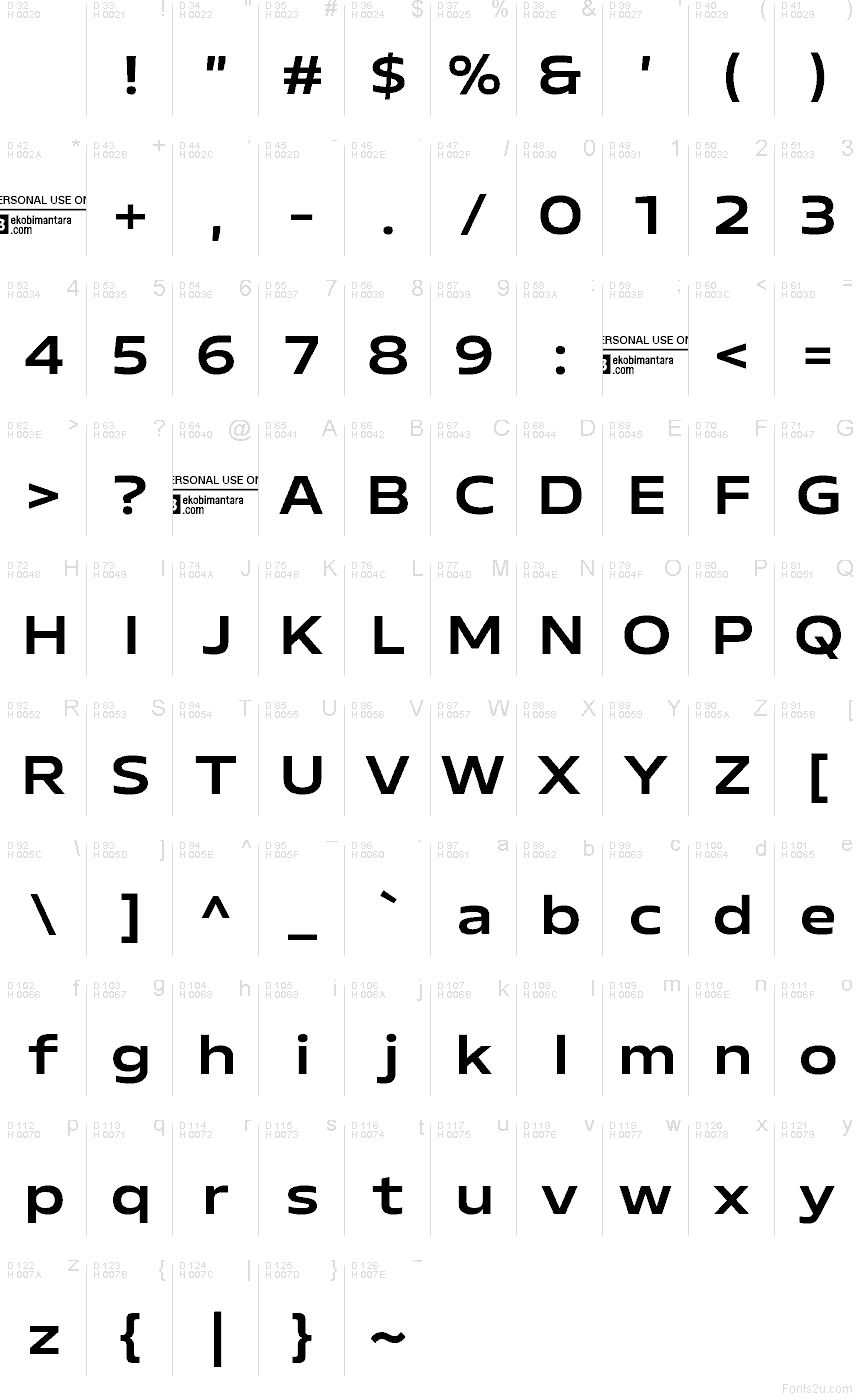
Profa Trial Bold Expanded, créée par Eko Bimantara, est une police sans empattement géométrique gratuite dotée d'une forte présence, d'une grande largeur et de courbes douces et conviviales. Les lettres paraissent modernes et directes plutôt que rigides, équilibrant des formes généreuses et arrondies avec des découpes nettes et bloc, ce qui confère à la police un rythme contemporain et affirmé.
Elle s'adapte parfaitement au branding, aux titres d'affiches, aux écrans de démarrage d'applications, au packaging et aux titres de magazines où une police gratuite doit paraître directe sans être froide. Grâce à des formes pleines et épurées, elle fonctionne également très bien pour les titres courts et les logos typographiques imposants qui nécessitent une forte présence avec peu de lettres.